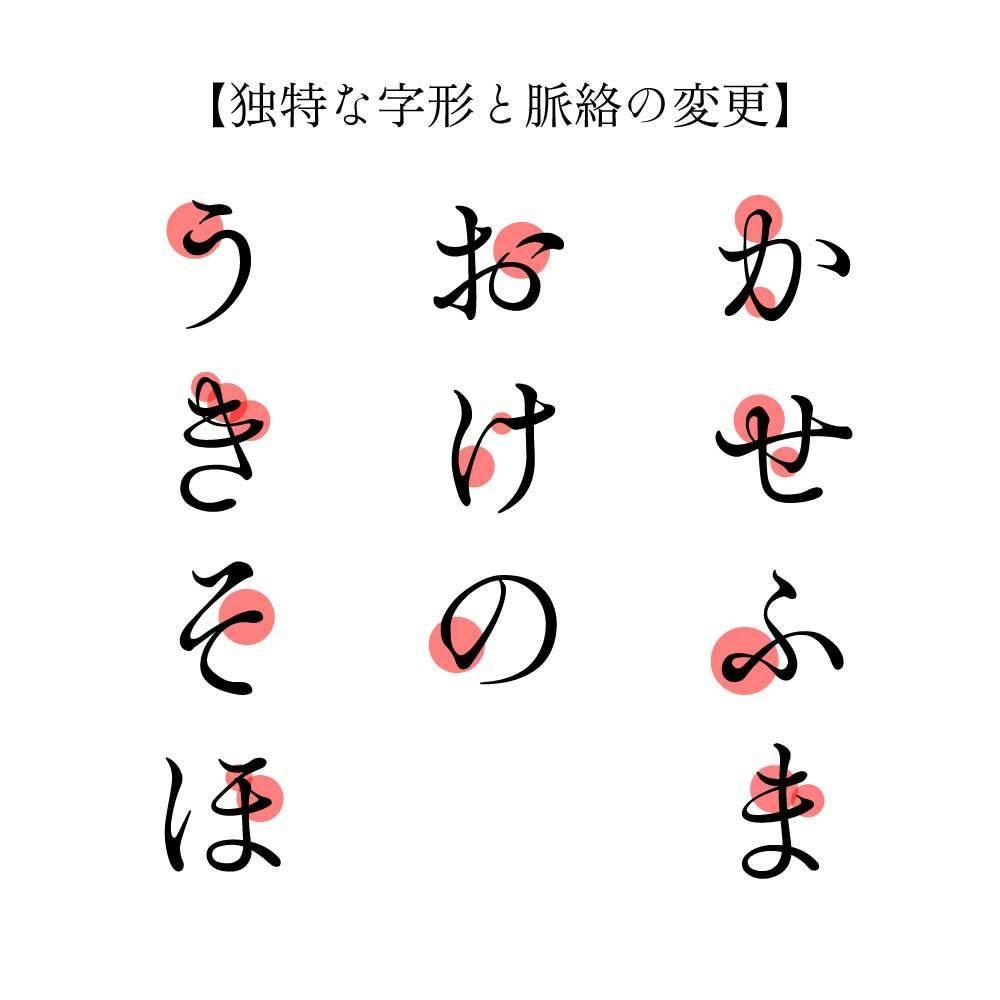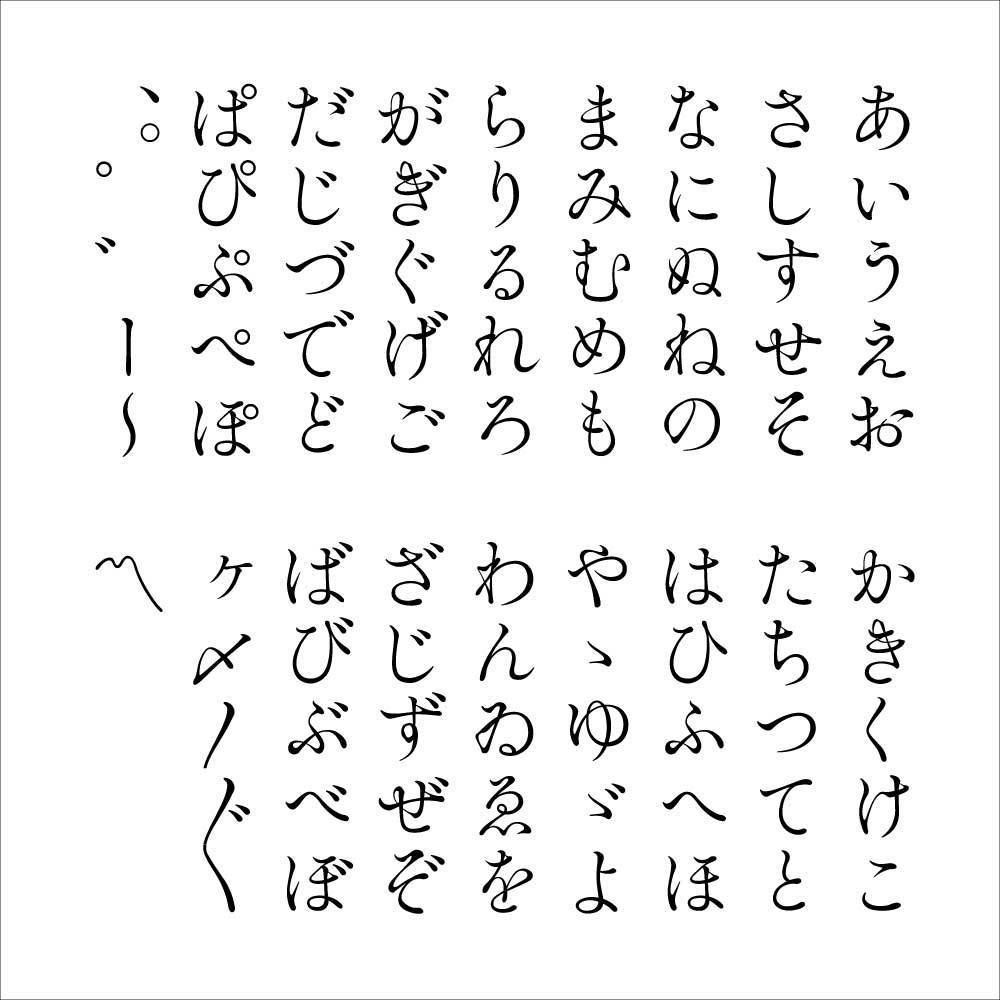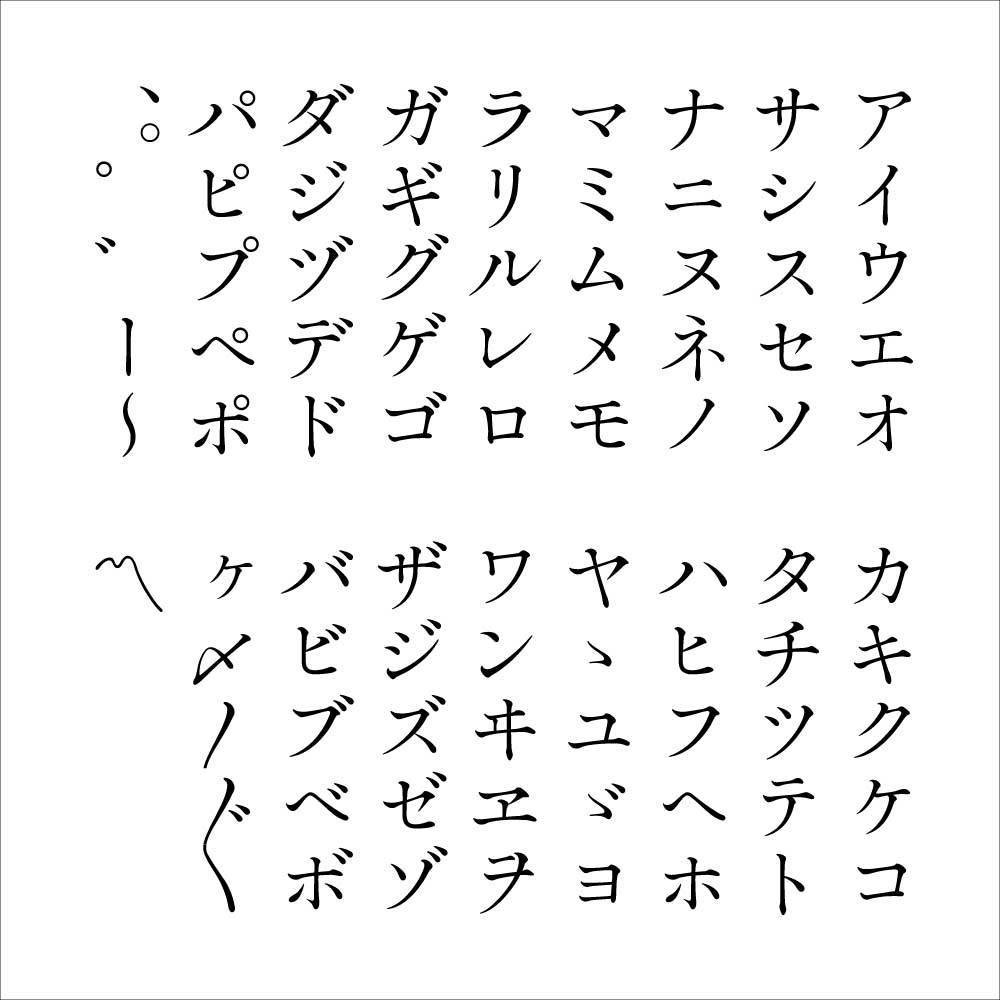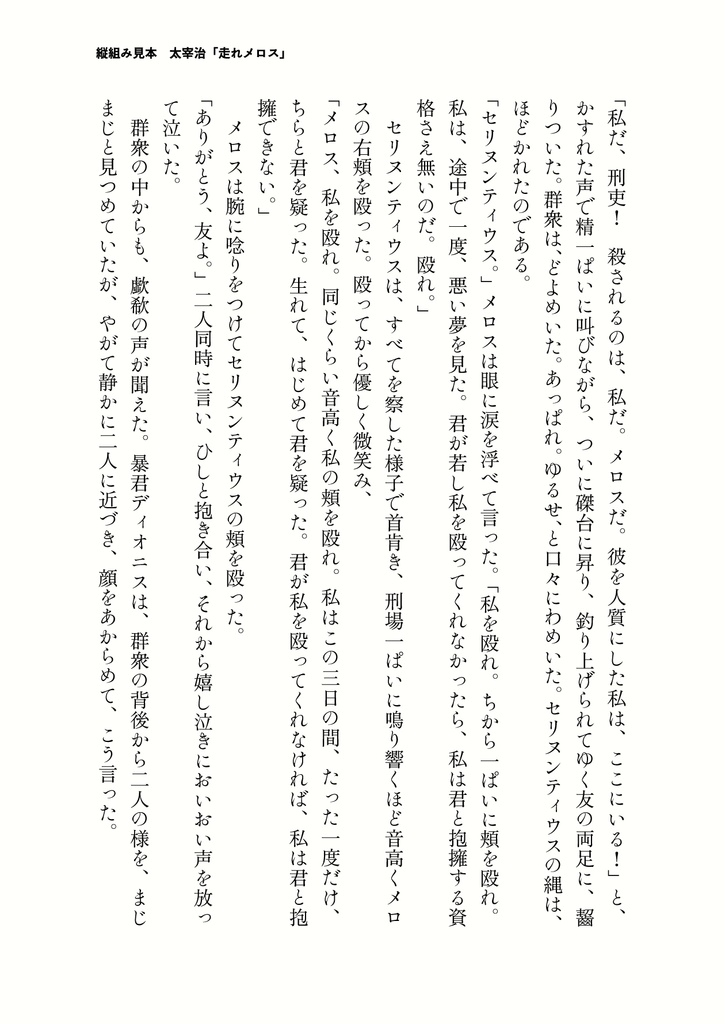
【フリーフォント】築豊明朝│オールドスタイルかな書体
■書体概要
築豊明朝(つくほうみんちょう)は築地五号系の伝統的な本文向け明朝体を意識して作られたかな書体です。
伝統な部分を残しつつ、一部のかなの脈絡を変更することで筆の動きや柔らかさをより強調させました。独特な字形もあり、本文だけではなく、見出しやタイトルでも使っても目を惹きつけられるかもしれません。
漢字や欧文は「ZENオールド明朝 Regular」からお借りしています。